Top 9 font chữ viết tay đẹp bạn không nên bỏ qua để tạo được một thiết kế ấn tượng
Font chữ viết tay đẹp là những font chữ đã được Việt hóa và phù hợp với những bộ gõ tiếng Việt trong máy tính của bạn. Sử dụng các font chữ này sẽ giúp tạo điểm nhấn ấn tượng cho tác phẩm thiết kế của bạn so với việc sử dụng các font chữ mặc định của hệ thống. Cùng tìm hiểu thêm ngay sau đây.
Font chữ viết tay đẹp thường được sử dụng trong việc thiết kế những ấn phẩm đồ họa, poster quảng cáo, thiệp mời, thiệp chúc mừng,… Nếu bạn đang tìm kiếm những mẫu font chữ viết tay đẹp thì hãy cùng tham khảo ngay danh sách bên dưới.
Top 9 font chữ viết tay đẹp và ấn tượng chuyên dùng cho thiết kế
Không để các bạn phải chờ lâu, chúng ta lập tức tìm hiểu vào các font chữ này ngay sau đây:
Amber Queen - Signature Font
Amber Queen Signature là font chữ viết tay đẹp và được sáng tạo dựa trên phong cách phá cách của những mẫu chữ ký chúng ta thường gặp ngoài đời. Sự nhấn nhá và góc cạnh là đặc điểm dễ nhận thấy ở font chữ này, chính vì vậy khi sử dụng font chữ Amber Queen sẽ giúp cho bản thiết kế của bạn có được điểm nhấn ấn tượng và thu hút sự chú ý của nhiều người xem.
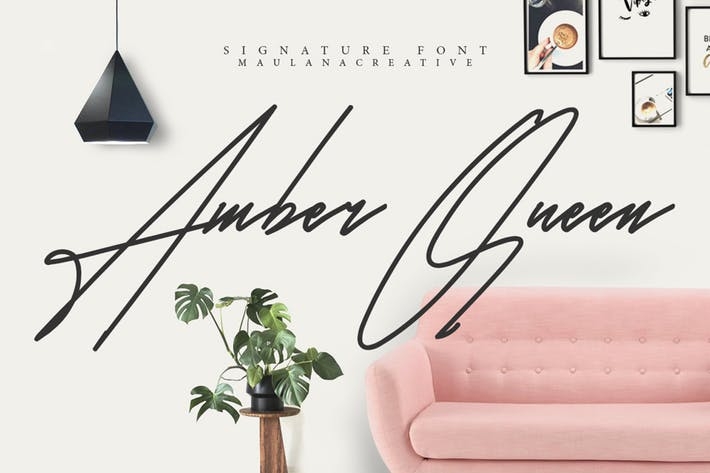
Leah Gaviota Hand Lettered
Font chữ viết tay đẹp và ấn tượng tiếp theo mà chúng tôi muốn giới thiệu đến với các bạn chính là font chữ Leah Gaviota Hand Lettered. Đây là font chữ kết hợp nhiều phong cách chữ viết vào trong một bộ font giúp tạo được sự phong phú, đa dạng và người dùng có thể sử dụng cho nhiều mục đích khác nhau (thiết kế poster, thiệp,…) đều phù hợp và đẹp mắt.
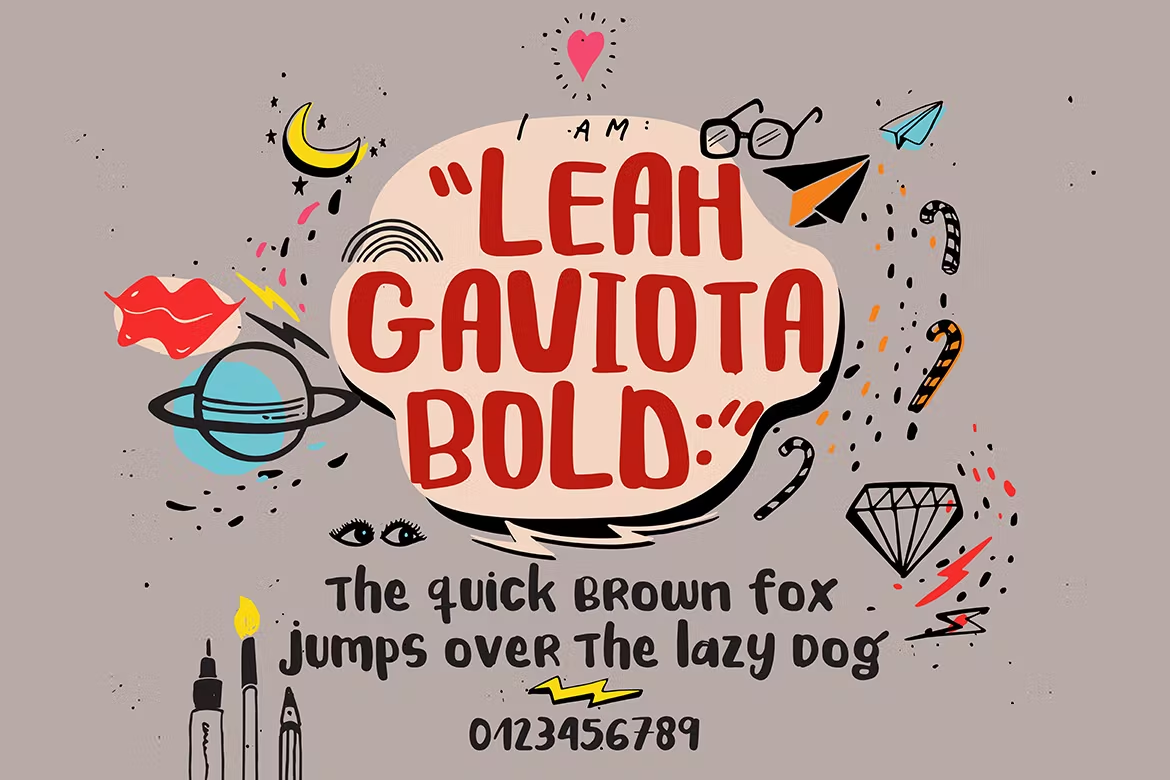
Một điểm ấn tượng nữa khi sử dụng font Leah Gaviota Hand Lettered đó là dù bạn chọn kiểu chữ in đậm, kiểu chữ nghiêng hay kiểu chữ thông thường thì phần hiển thị cũng rất đẹp. Đặc biệt bộ font này còn có thêm 100 icon được thiết kế hài hòa để bạn có thể làm cho bản thiết kế của mình thêm phần bắt mắt.
Buffalo Handwritten Font
Buffalo là một font chữ viết tay đẹp và được rất nhiều người dùng ưa thích sử dụng để thiết kế logo, bao bì sản phẩm. Font chữ này có sự mềm mại, không tạo cảm giác cứng ngay cả khi bạn sử dụng chế độ Bold (in đậm). Khi sử dụng font Buffalo thì dù bạn viết theo kiểu thông thường hay kiểu chữ hoa thì con chữ cũng đều có những nét nhấn nhá rất uyển chuyển và bắt mắt.
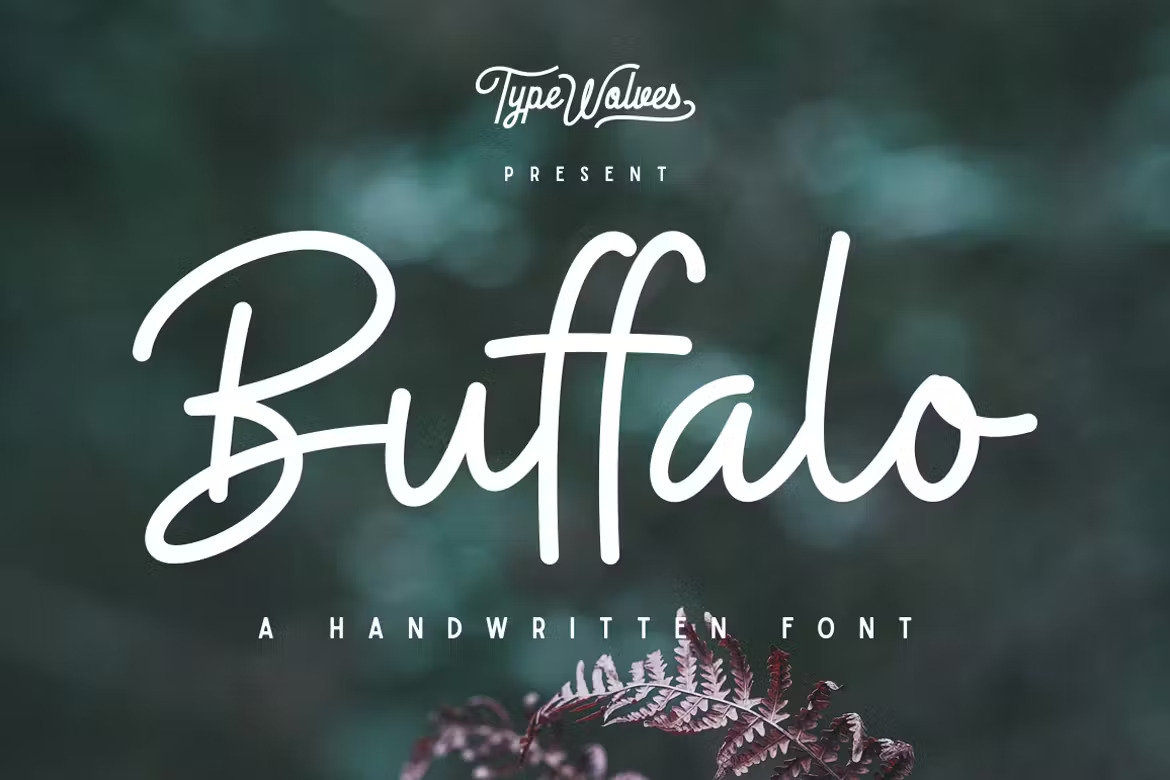
Gineva Script Font
Nếu bạn đang muốn tìm font chữ viết tay đẹp có sự kết hợp của yếu tố thư pháp với những nét mảnh và dày đan xen nhau thì Gineva Script là một bộ font rất phù hợp để lựa chọn. Đây là bộ font chữ được sử dụng rất nhiều trong việc thiết kế các poster quảng cáo hoặc bao bì của sản phẩm, những thông điệp trên các tấm thiệp mừng,… Hãy thử tải về bộ font Gineva Script để tự mình tạo nên một thiết kế ấn tượng xem sao nhé.
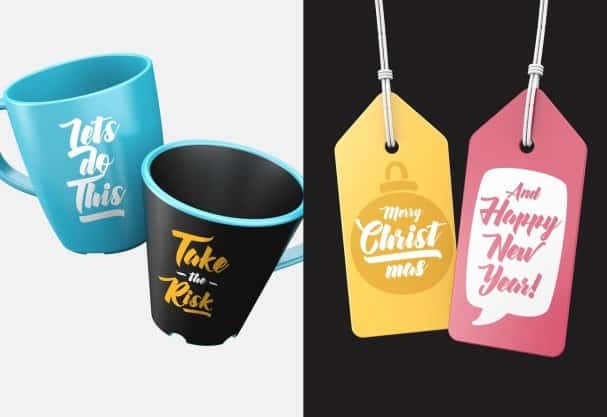
Better Saturday
Better Saturday là bộ font chữ viết tay đẹp và tạo cảm giác ấn tượng như khi bạn đang nhìn vào những tác phẩm thư pháp hiện đại. Font chữ này được tạo thành bởi những đường nét đơn giản, thậm chí có phần nguệch ngoạc nhưng lại cực kỳ tinh tế và tạo cảm giác thoải mái cho người xem khi theo dõi. Đây là bộ font rất phù hợp để bạn có thể tạo nên những tấm thiệp đáng yêu dành tặng người thân và bạn bè đấy.
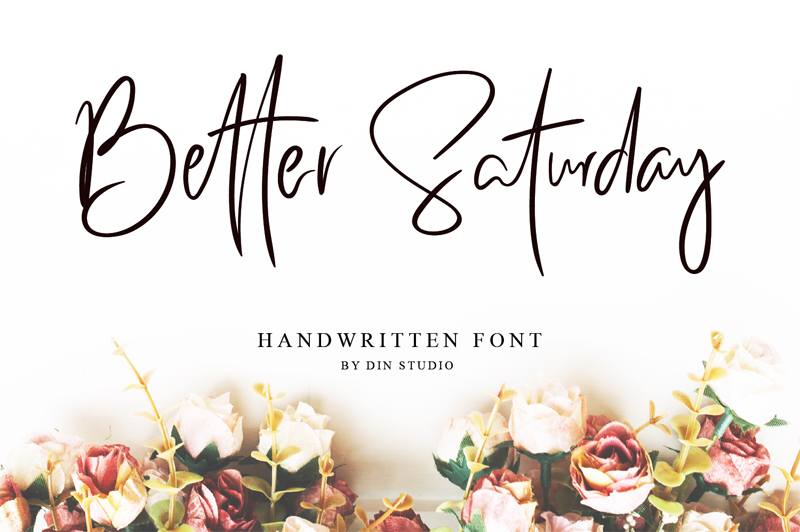
Diandra Signature Font
Đây tiếp tục là một bộ font chữ viết tay đẹp và ấn tượng theo kiểu thư pháp với những đường nét thanh mảnh và các nét chấm phẩy độc đáo y hệt như một người đang vung bút. Hiện tại thì Diandra Signature Font thường được nhiều người sử dụng để tạo những tấm thiệp độc đáo hoặc tạo watermark đính vào các tác phẩm kỹ thuật số của mình, tạo phong cách cá nhân độc đáo và thú vị.
Kikuri Font
Sẽ thật sai lầm nếu trong danh sách những font chữ viết tay đẹp và độc đáo không có sự xuất hiện của Kikuri - một font chữ thật sự ấn tượng và đặc sắc. Người xem khi nhìn vào một thiết kế có sử dụng font chữ Kikuri sẽ có cảm giác nét chữ như những dòng nước, ngưng tụ chỗ nhiều chỗ ít nhưng tổng thể lại tạo được sự hài hòa và cực kỳ mềm mại, uyển chuyển.
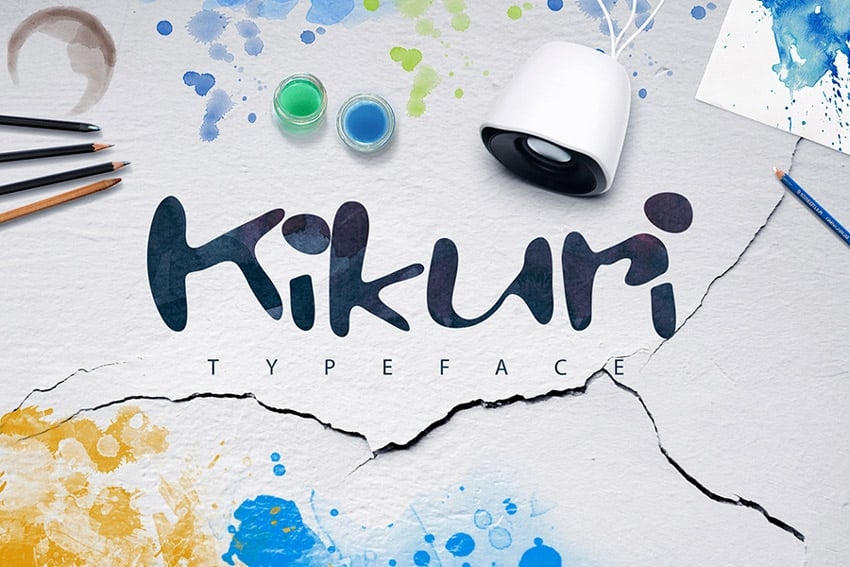
Handster Typeface
Khi nhìn vào những mặt chữ trong bộ font Handster Typeface người xem sẽ có ấn tượng giống như đây là những con chữ được viết nên bởi một cây bút lông nhúng vào màu nước với độ đậm nhạt khác nhau. Chính phong cách thiết kế ấn tượng này giúp Handster Typeface trở thành một trong những font chữ viết tay đẹp được rất nhiều người sử dụng khi thiết kế và chỉnh sửa các tác phẩm đồ họa của mình.
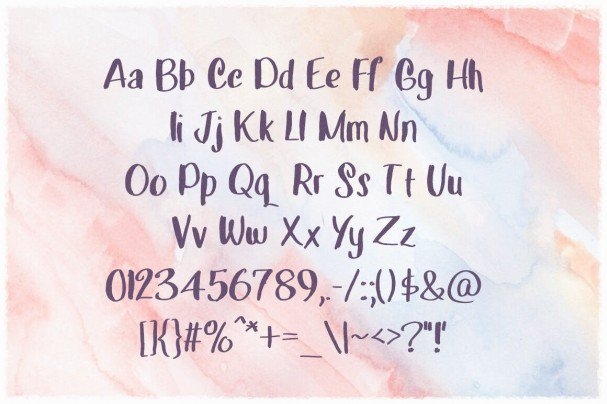
Lote Santos Font
Đây là một bộ font chữ viết tay đẹp và cho người xem cảm giác thân thuộc như khi được trông thấy chữ viết phấn trên nền bảng đen như tuổi học sinh năm nào. Những nét nhấn nhá, đậm nhạt khác nhau tạo sự ấn tượng và giúp thu hút người xem khi nhìn vào các tác phẩm được sử dụng font chữ Lote Santos.
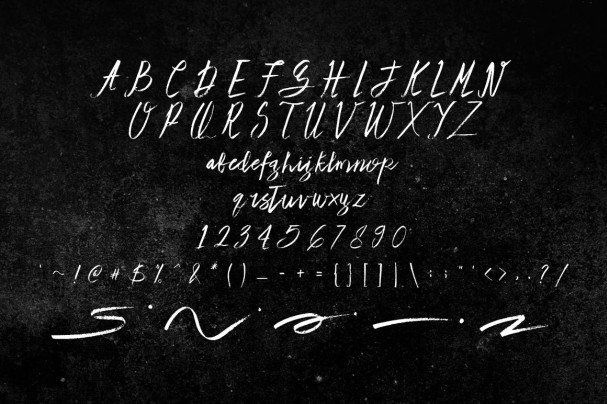
Cách sử dụng các font chữ viết tay đẹp hiệu quả nhất
Để có thể sử dụng các font chữ viết tay đẹp một cách hiệu quả nhất cho các tác phẩm thiết kế của mình thì có các lưu ý sau các bạn nên ghi nhớ:
- Tìm hiểu kỹ về cách thêm font chữ vào máy tính: Đầu tiên để có thể sử dụng các font chữ viết tay cho thiết kế của mình thì bạn cần tìm hiểu về cách thêm font chữ vào máy tính. Đây là bước đầu tiên để việc sử dụng các font chữ này đạt hiệu quả cao nhất. Các bạn có thể click vào đây để tham khảo về cách thêm font chữ vào máy tính.
Tạm kết